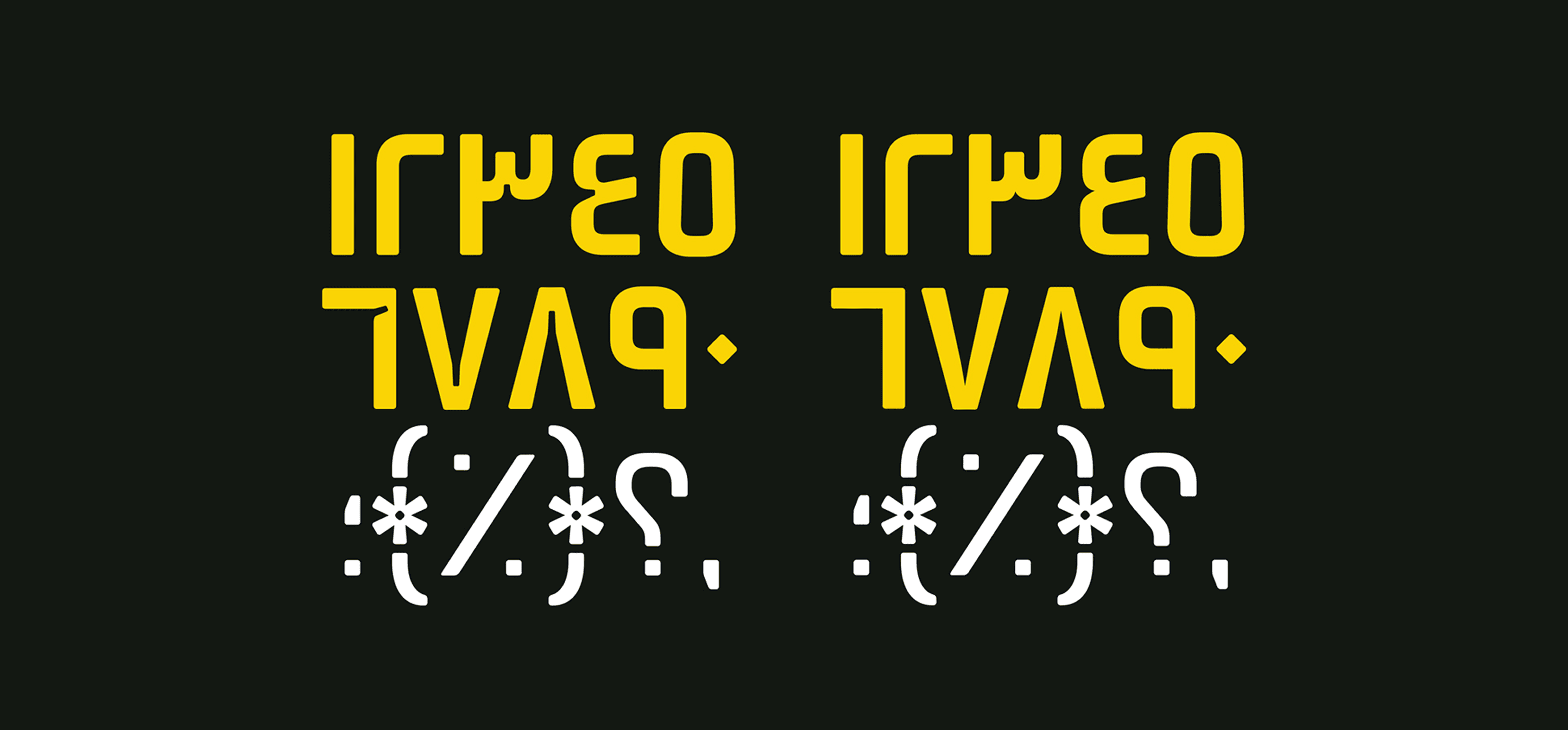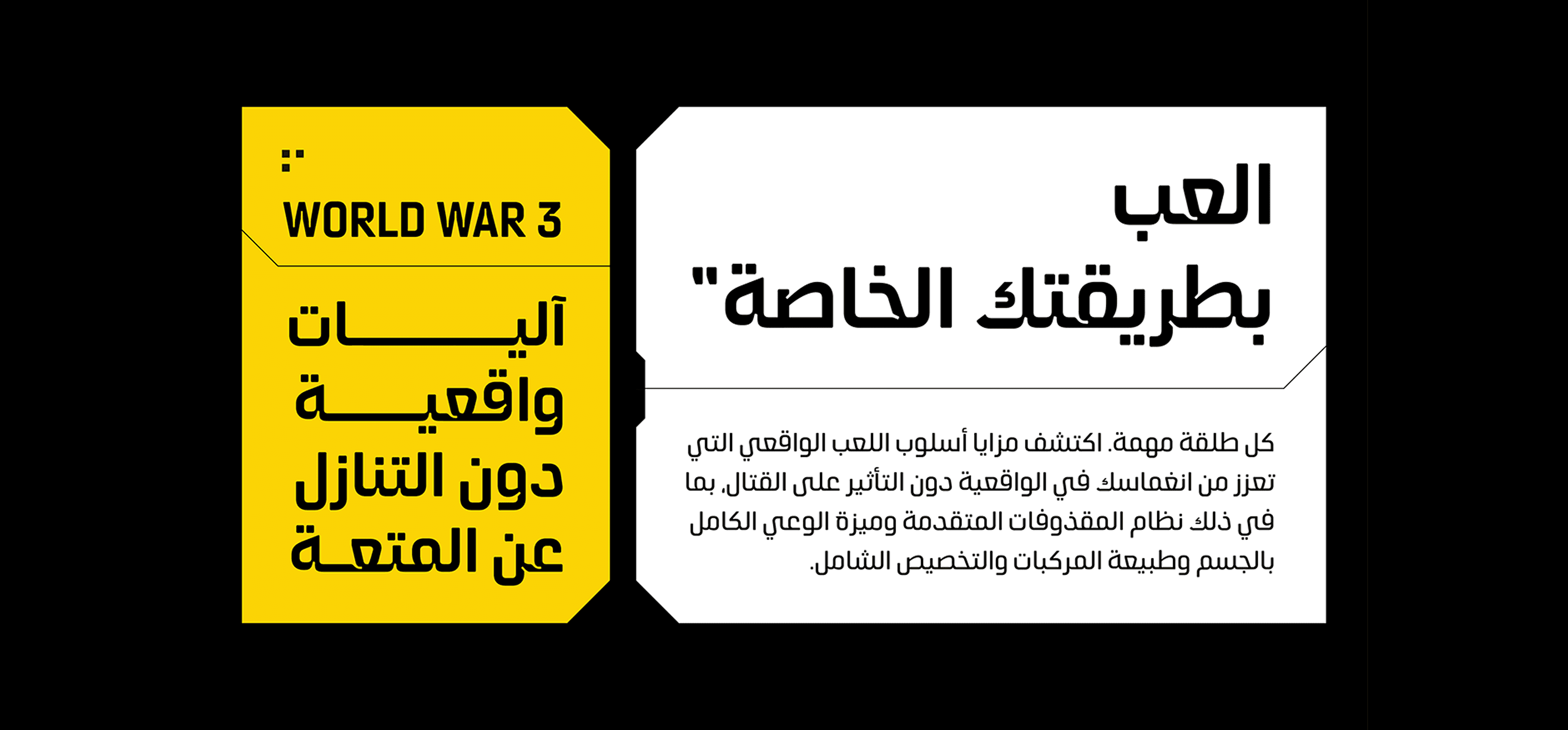
تم تصميم خطوط WW3 حصريًا للعبة الفيديو "World War 3" بالتعاون مع شركة The 4 Winds Entertainment.
قمنا بتصميم الخطوط العربية لتتناسق مع الخطوط الأصلية للغات الأخرى، مما يضمن تجربة بصرية متكاملة ومتناسقة داخل اللعبة.Ask ChatGPT